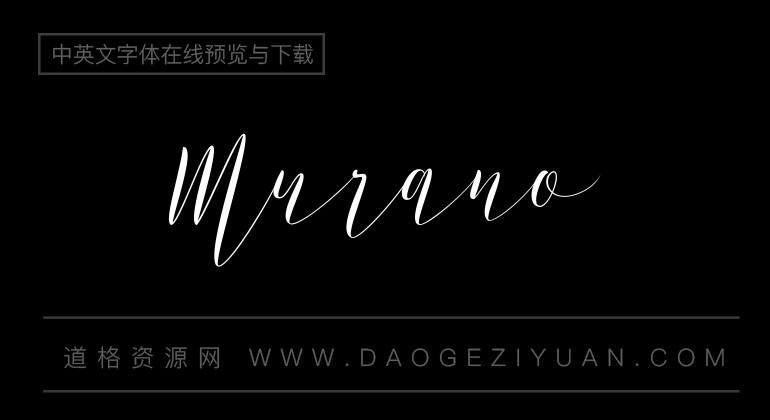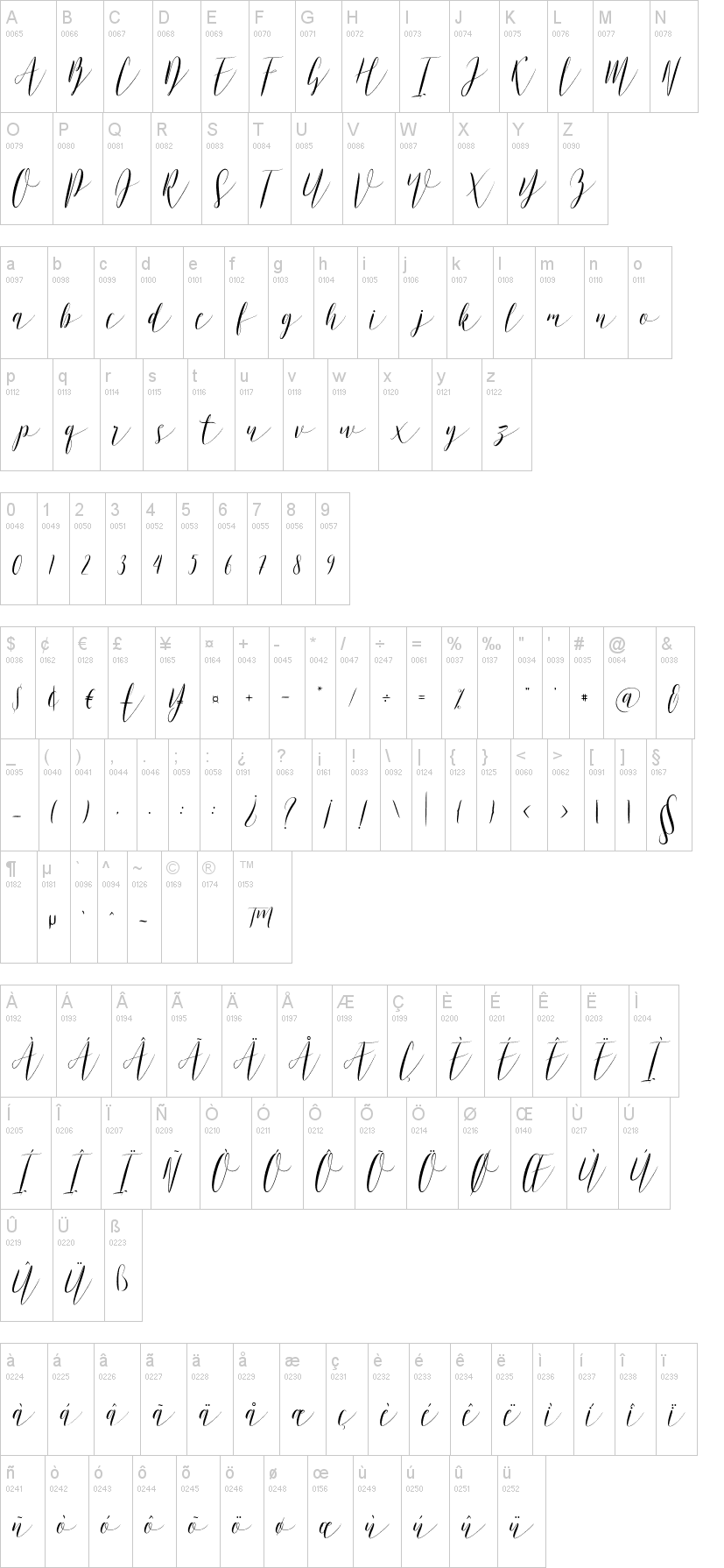
Murano 是一种非常漂亮的手写风格字体,由 Laura Worthington 设计。这种字体风格充满了艺术气息,适用于各种设计项目,例如海报、卡片、名片、标志、包装等等。 Murano 字体有三种不同的版本:常规、粗体和斜体,每个版本都具有相同的美妙细节和流畅的线条。字母间距和字距非常协调,让 Murano 字体非常易于阅读和使用。它的设计风格适合多种场景,从优雅的正式场合到惬意而轻松的休闲场合,Murano 字体都能够完美地展现出来。内容介绍
Murano是一款非常不错的手写艺术字体,具有很好的视觉感,适合于文化类的宣传设计、商业类品牌的广告和产品包装设计以及个性化文字排版等较多场景。